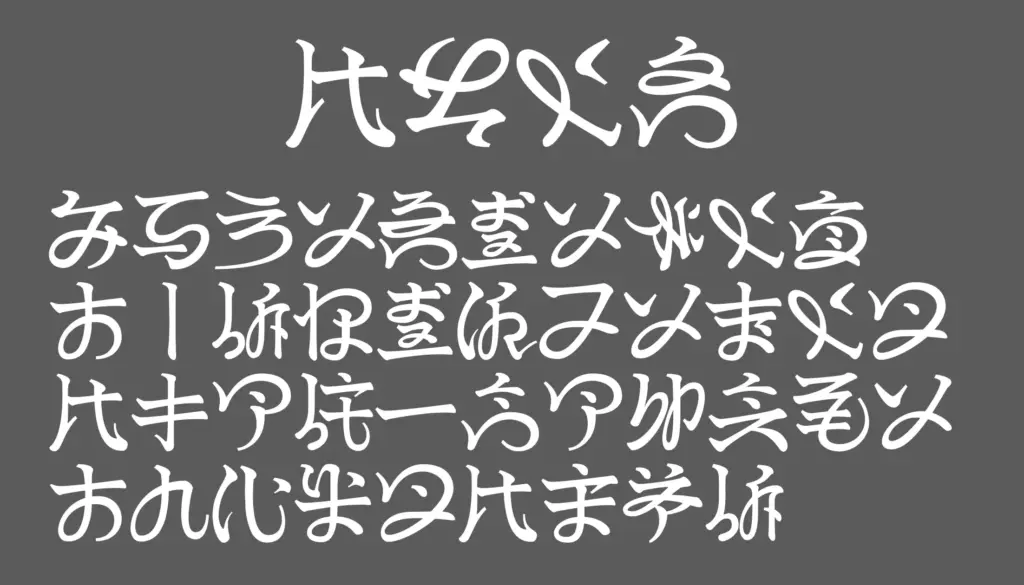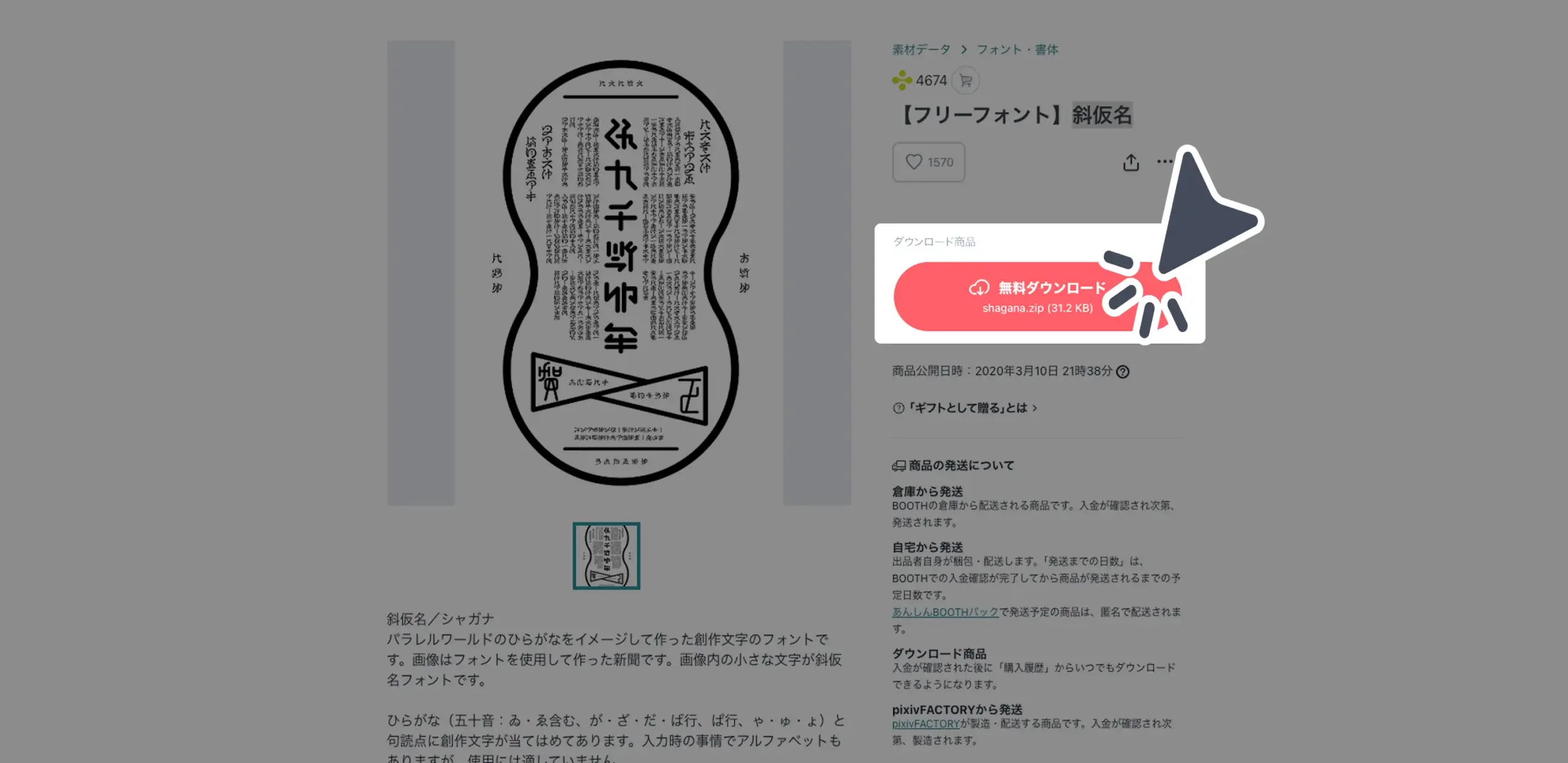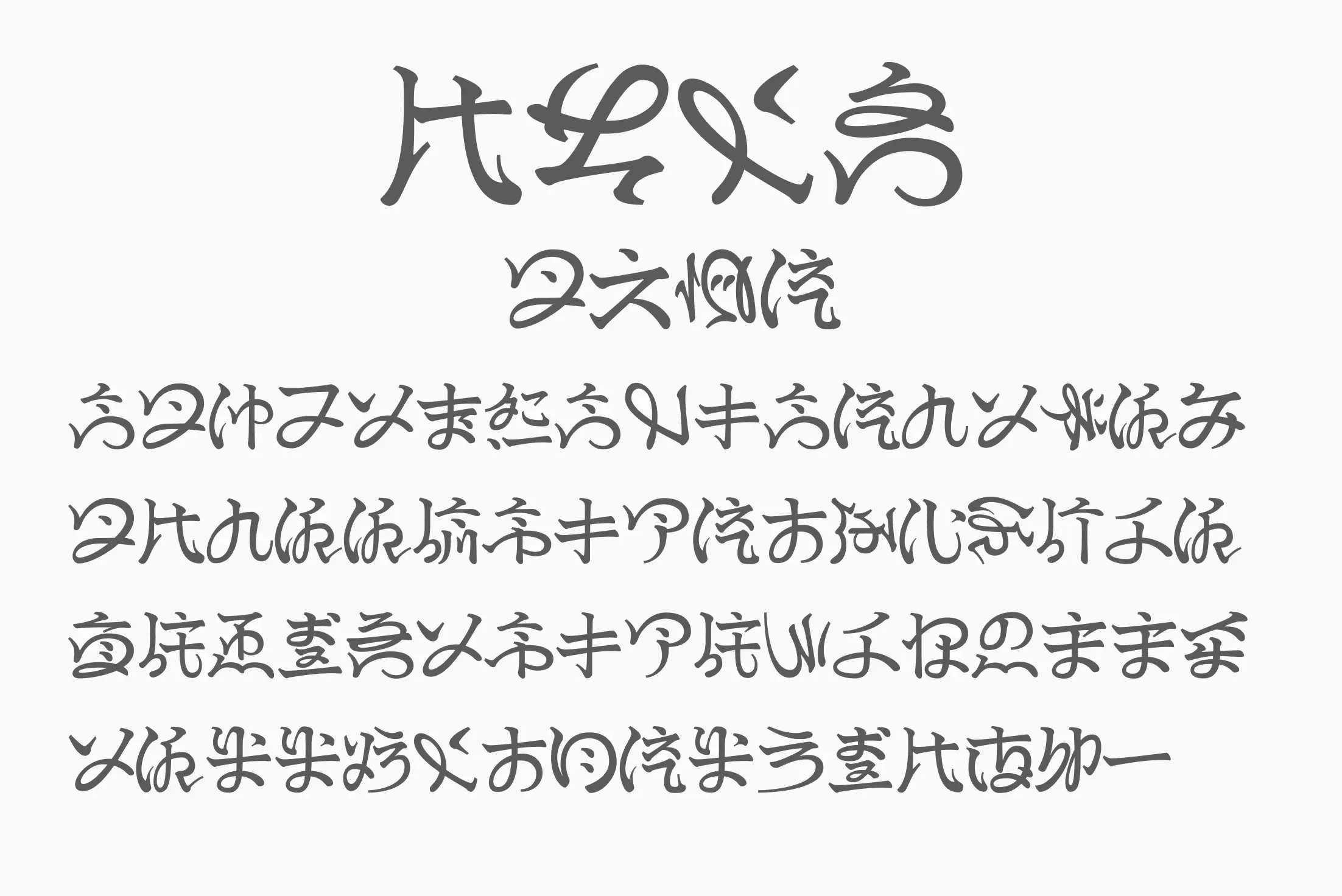
「パラレルワールドのひらがな」をテーマに制作された、完全創作文字の日本語フォントです。斜めに傾いた文字はどこか異世界的で、手書きでもなく明朝・ゴシックでもない、唯一無二の空気感をまとっています。新聞風レイアウトや縦書き作品にハマりやすく、アートブックやMV・ZINE系デザインにおすすめです。
斜仮名